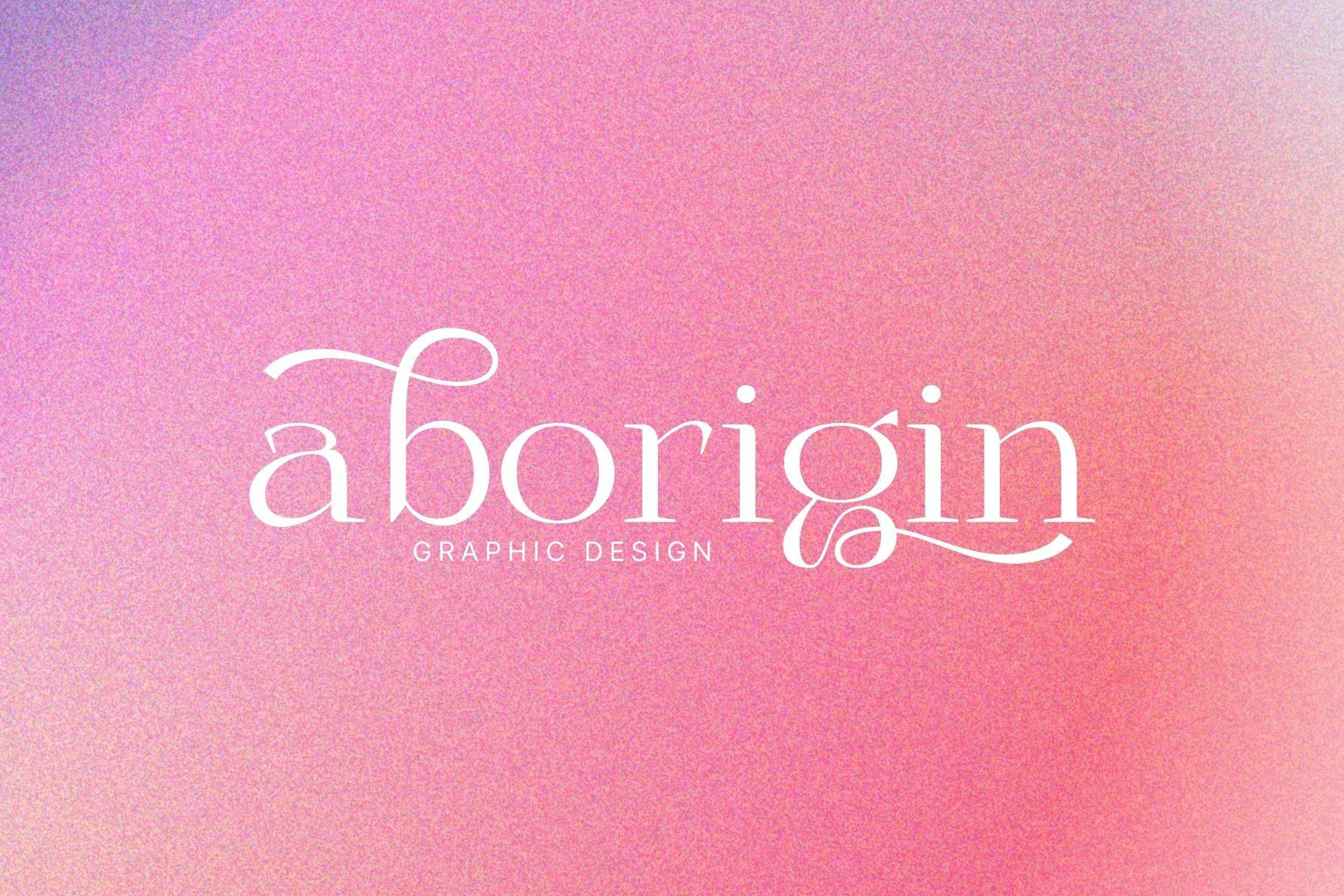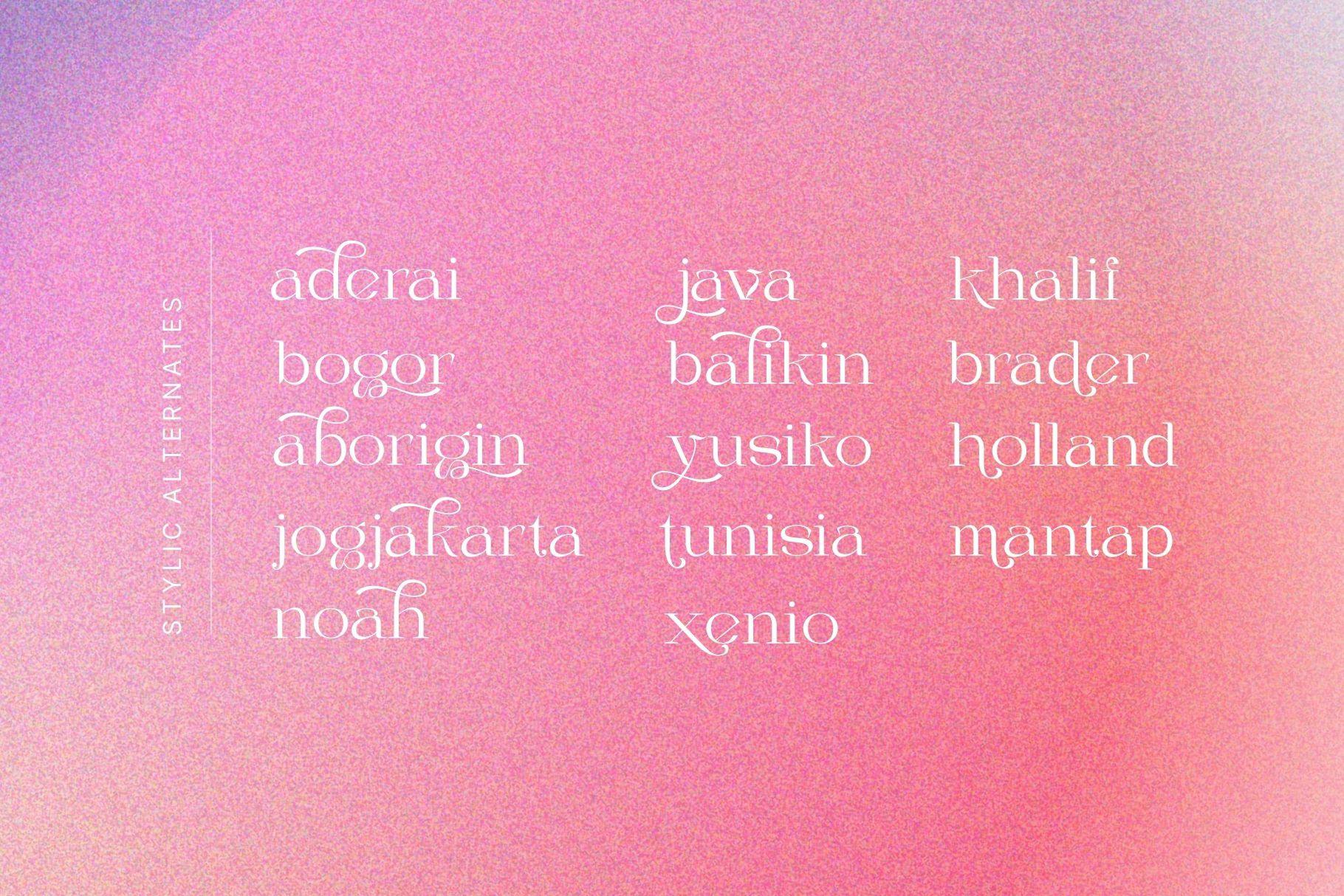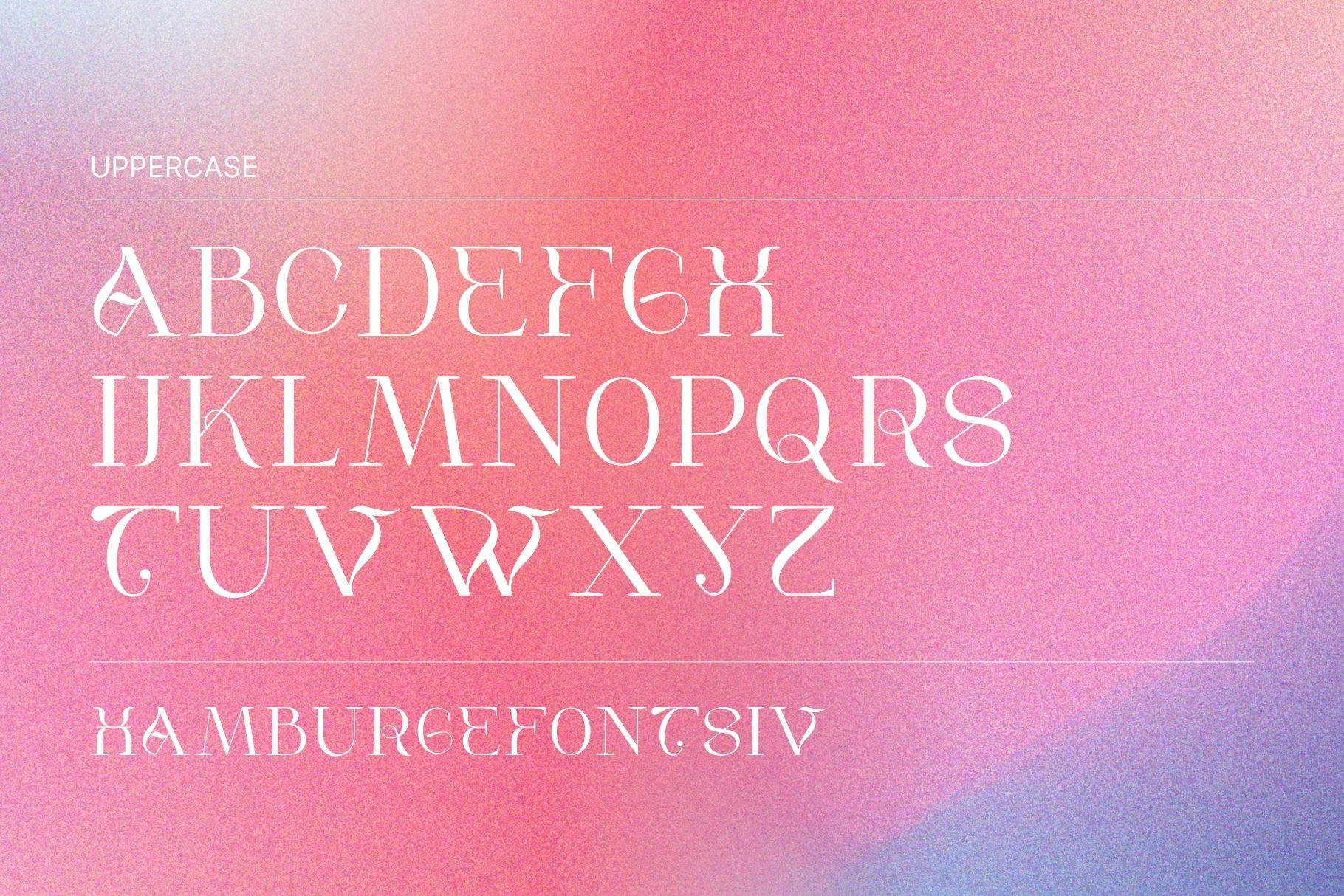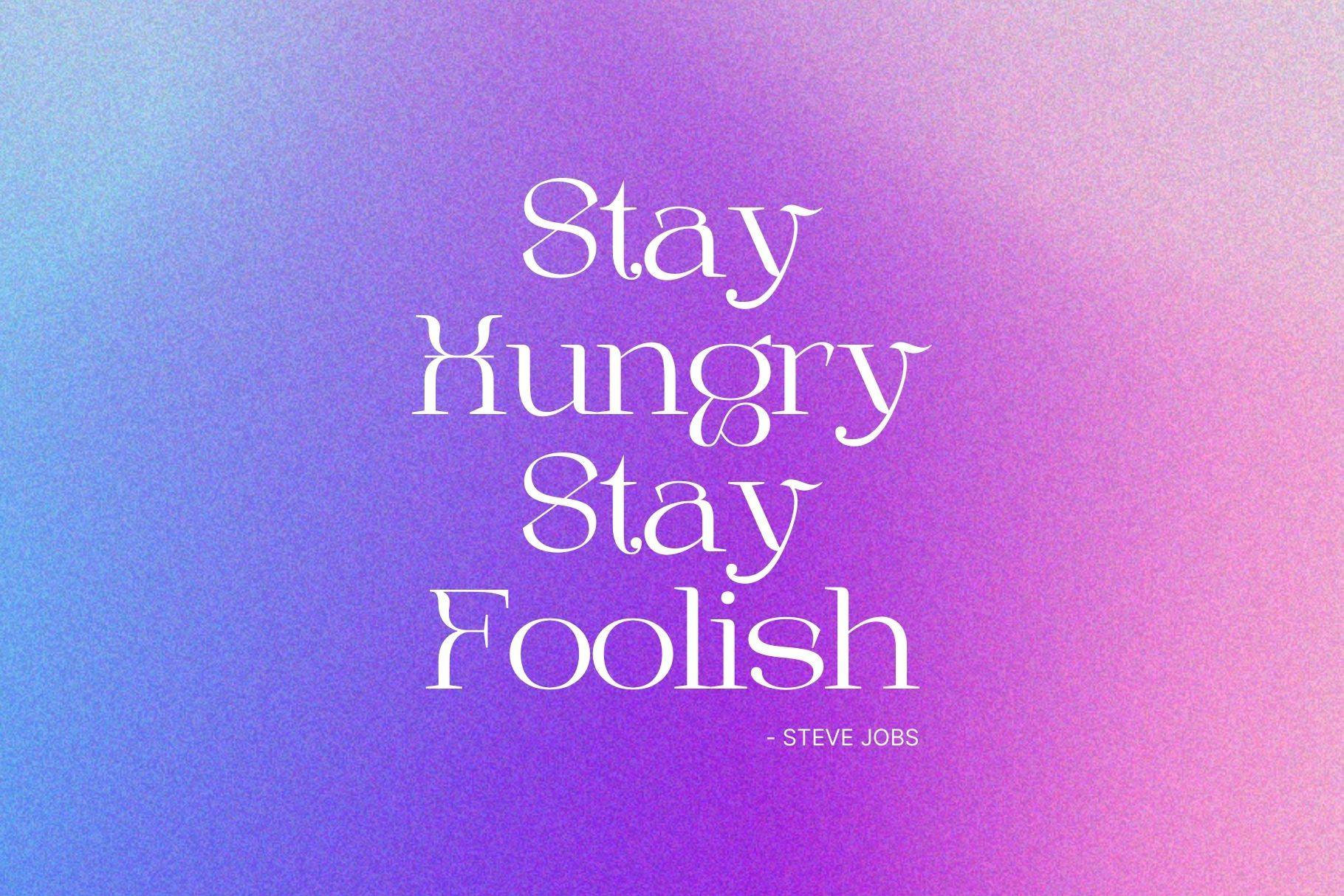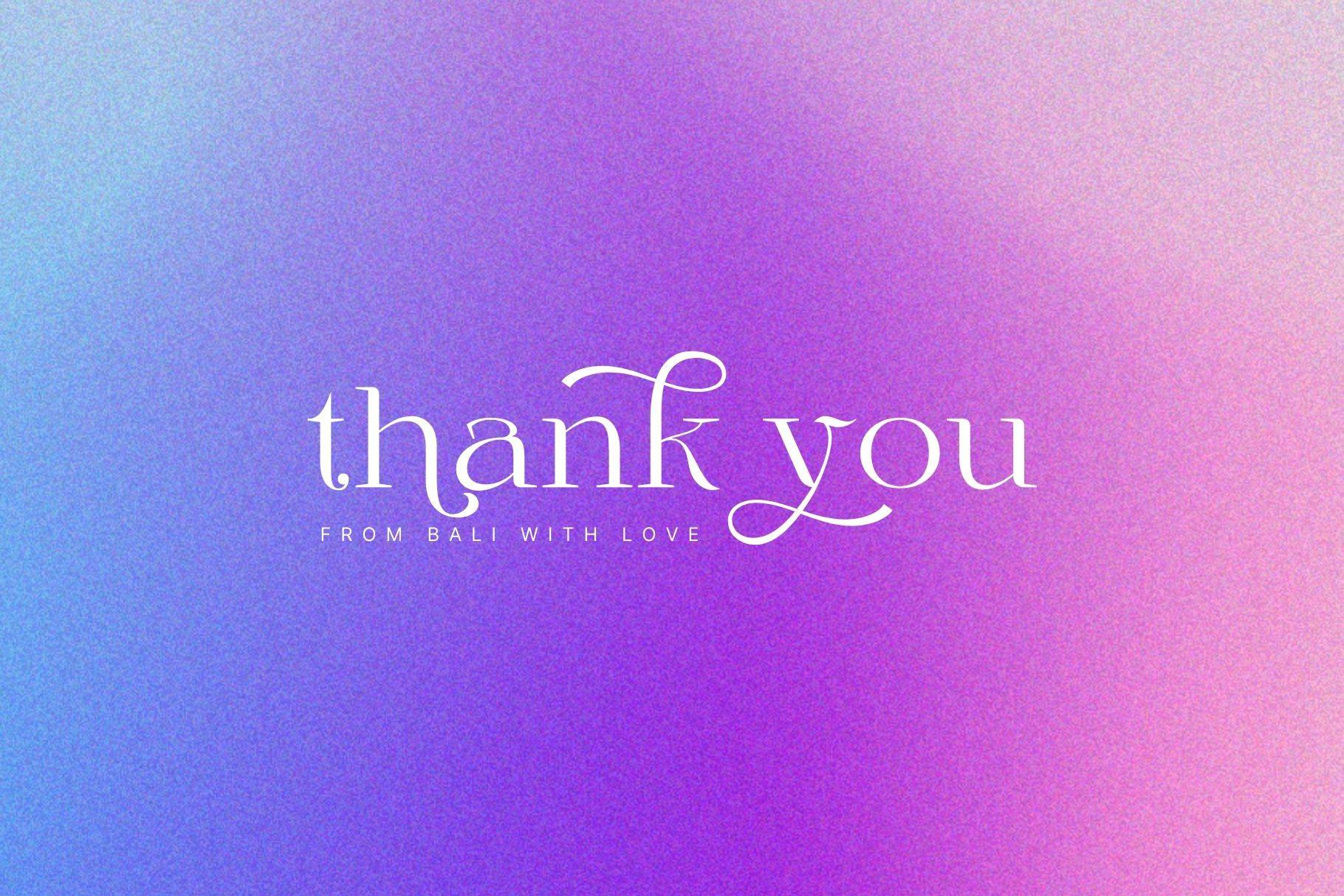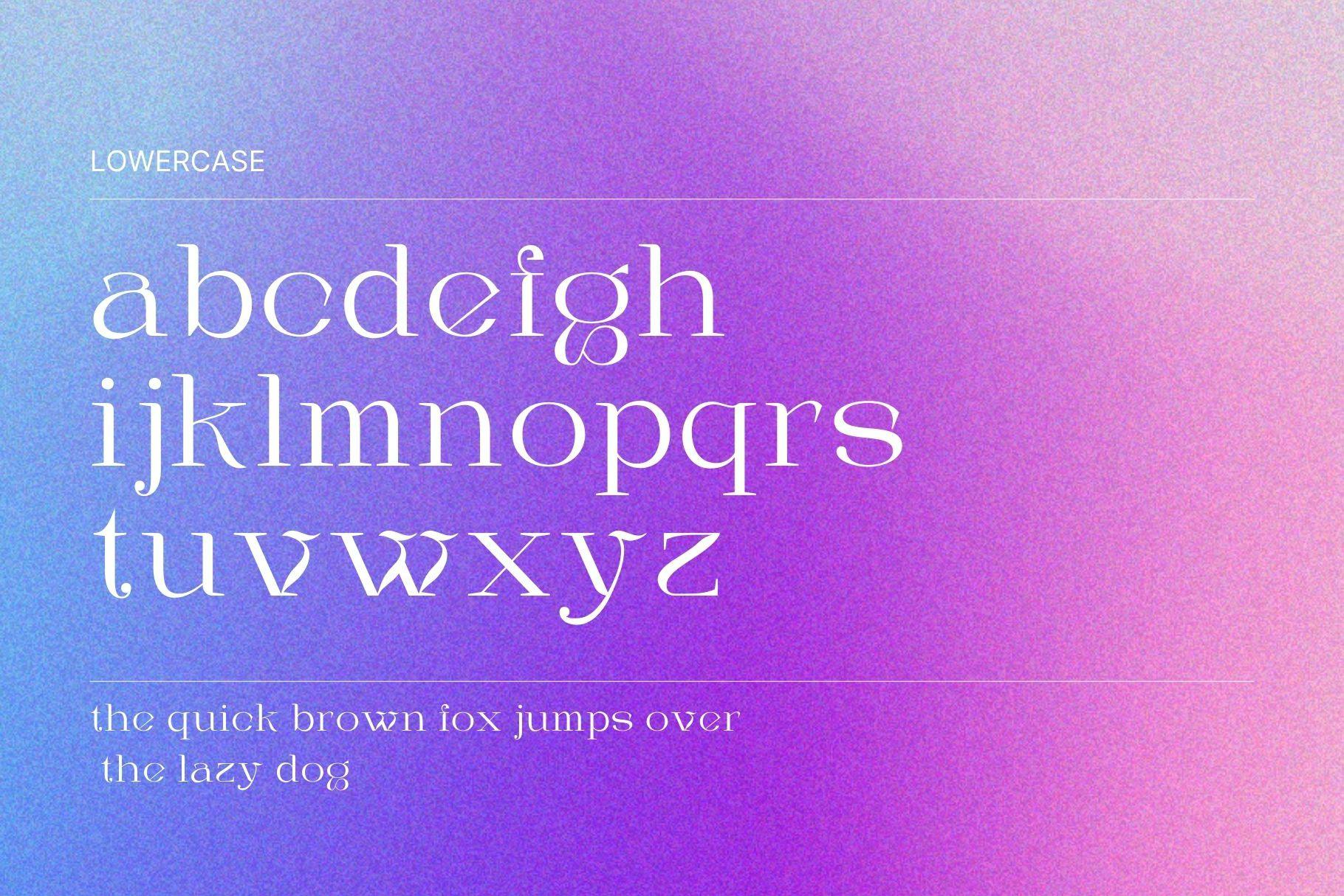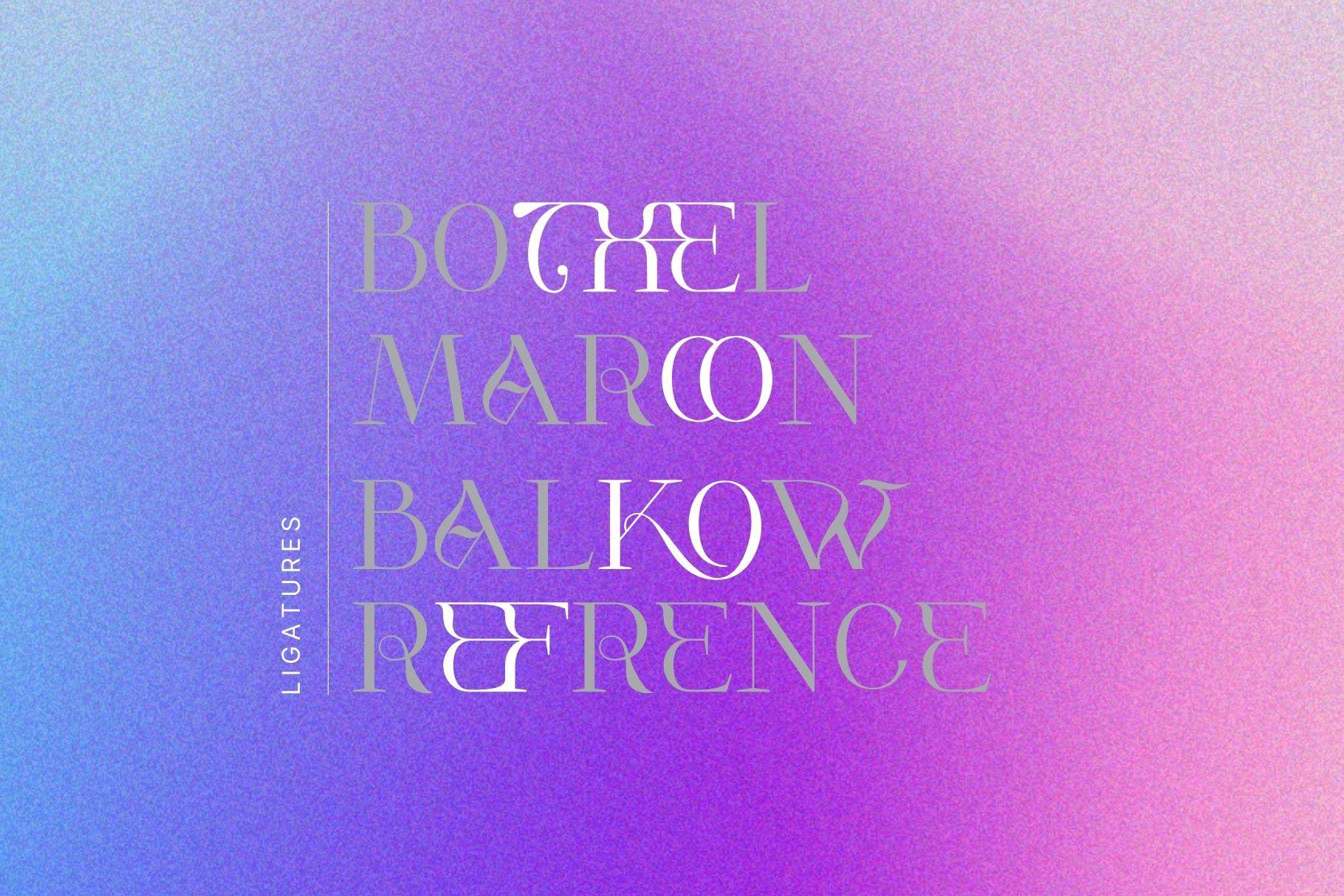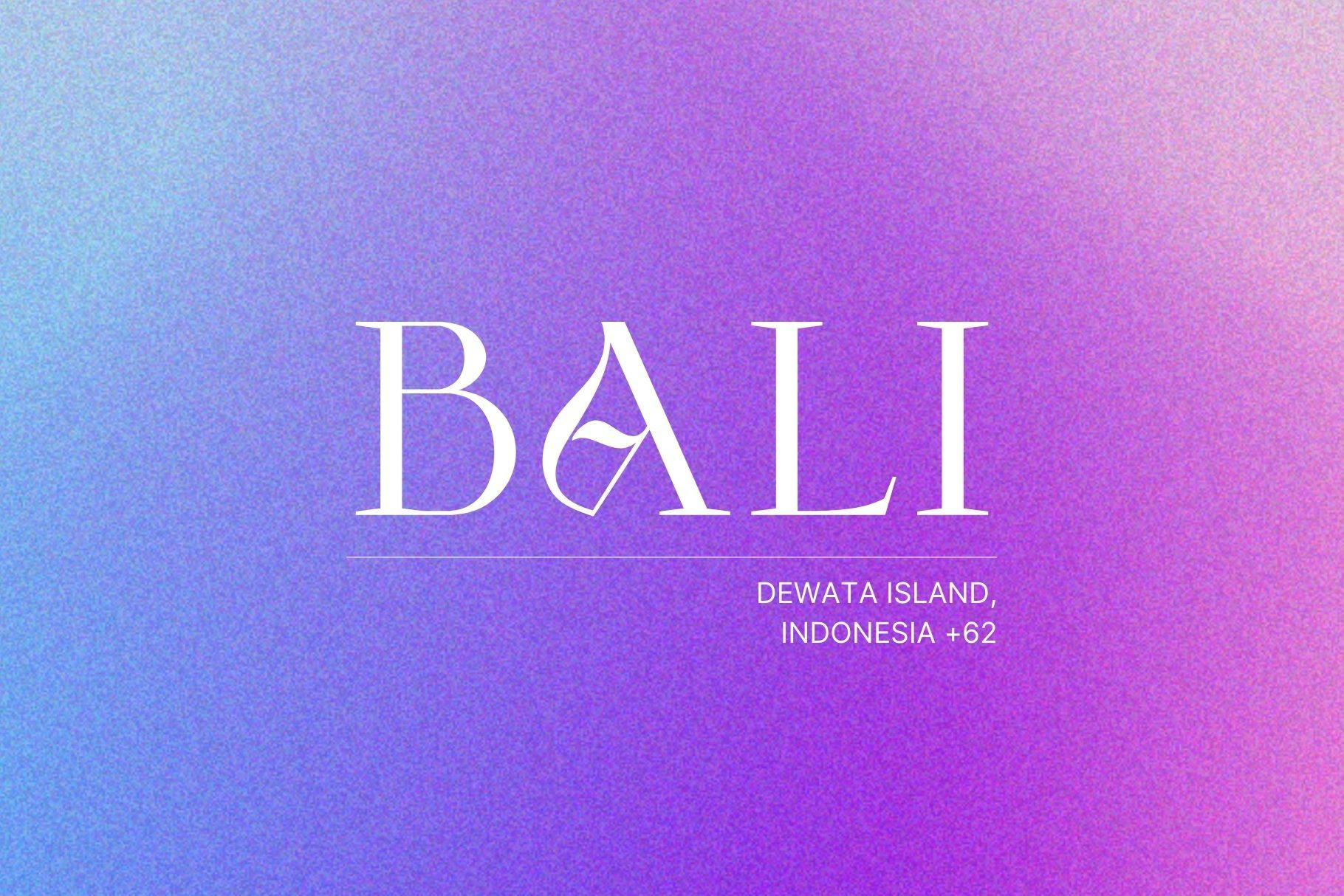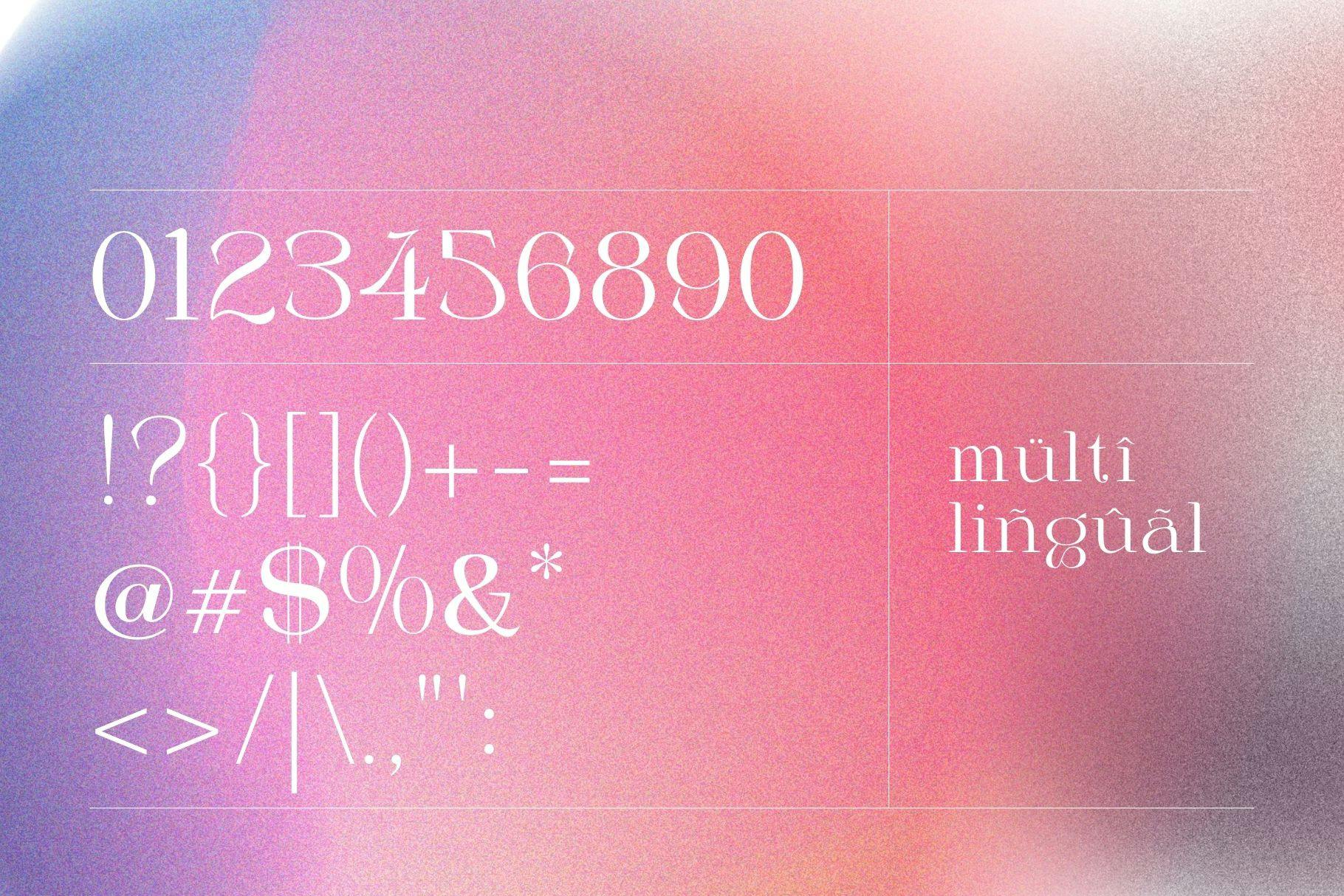
فونت Vako Mave یک فونت سریف مدرن است که هم به یاد ماندنی و هم شیک میباشد. این فونت برای برندینگ مرتبط با مد یا طراحی ویرایشی ایدهآل است و ویژگیهای مردانه و زنانه را به خوبی نمایش میدهد.